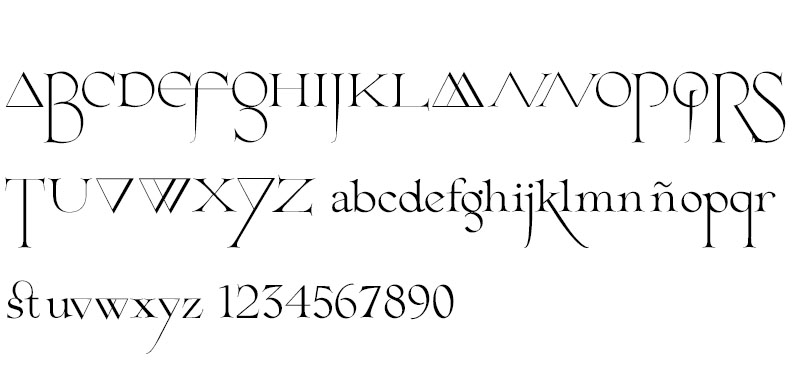
La tipografía gratuita “Cantique” ha sido diseñada por Sébastien Hayez tras muchos años de experiencia en el sector del diseño. Entre todas las habilidades del artista destacan la dirección de arte, el diseño gráfico y de tipografía, la ilustración, la escritura y la investigación independiente.
En sus 17 años de carrera en muchos aspectos diferentes del diseño, el francés ha conseguido plasmar sus trabajos en libros, periódicos… y ha dado conferencias en ciudades como Lyon. La tipografía gratuita “Cantique” es fresca, ligera y muy atractiva. No pierdas el tiempo y hazte ya con ella.
La tipografía gratuita “Cantique” diseñada por Sébastien Hayez tiene caracteres de caja alta y caja baja.
The free font “Cantique” has been designed by Sébastien Hayez after many years of experience in the design sector. Among all the skills of the artist include art direction, graphic design and typography, illustration, writing and independent research.
In his 17-year career in many different aspects of design, the french has managed to translate his work into books, newspapers … and has given lectures in cities such as Lyon. The free typography “Cantique” is fresh, light and very attractive. Stop waisting your “type” and get it now.
The free typography “Cantique” designed by Sébastien Hayez has upper case and lower case characters.